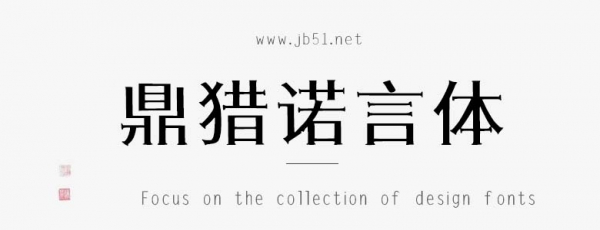
鼎獵諾言體由鼎獵字庫出品的藝術字體,以宋體為藍本衍化的創(chuàng)意字體,整體有棱角但內里有筋骨,具有很好的視覺感,適合應用于藝術設計、平面宣傳設計、網頁設計,書法字帖等領域。有需要的朋友快來本站下載使用吧。
鼎獵諾言體,是一款以宋體為藍本衍化的創(chuàng)意字體,整體有棱角但內里有筋骨,有著一諾千金和一言九鼎的穩(wěn)健,也有自主自立的棱角。鼎獵諾言體適合美食餐飲、文化藝術展覽、企業(yè)文化,以及封面雜志海報、餐飲茶飲、美妝護膚等各個行業(yè)。
考慮到字體應盡可能滿足各類型的需求,鼎獵西大體以簡體中文漢字編碼國家標準(GB2312編碼)為標準,共計設計了多達7415個字符,其中漢字6769個。可以滿足絕大部分印刷設計等要求。